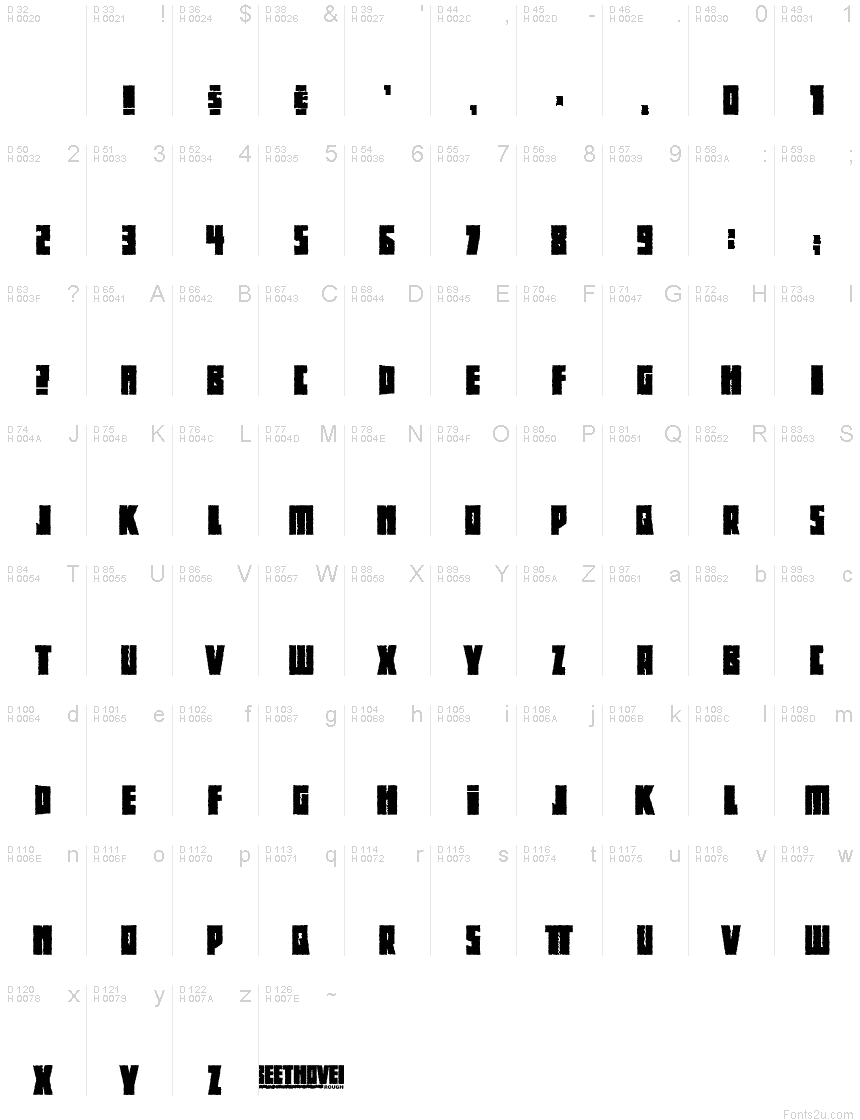
يُعد خط Beethoven Rougher من J.F.Y.Daniel Gauthier في GautFonts خط عرض (Display) مجانياً ذا مظهر متآكل، يبدو وكأنه سُحب على خرسانة. تشكل المستطيلات السوداء الضخمة الحروف، بينما تضفي حوافها المتآكلة وغير المنتظمة ملمساً خاماً وصاخباً. إنه خط جريء وكتلي ولا يمكن تجاهله، مثل قالب رسم (Stencil) استُخدم أكثر من اللازم.
استخدم Beethoven Rougher بأحجام كبيرة على الملصقات، وأغلفة الألبومات، وتصاميم الرعب، والمجلات (Zines)، وعناوين الألعاب، أو في هوية علامات الشارع التجارية (Streetwear) لإضفاء نبرة جريئة و"أندرغراوند" فورية. يعمل هذا الخط المجاني بشكل رائع عندما تبقي النصوص المصاحبة نظيفة وصغيرة؛ جرب إقرانه بخط بسيط بلا زوائد (Sans-serif) مع ترك مساحة كافية، حتى تتمكن حوافه الخشنة من إظهار قوتها الحقيقية.